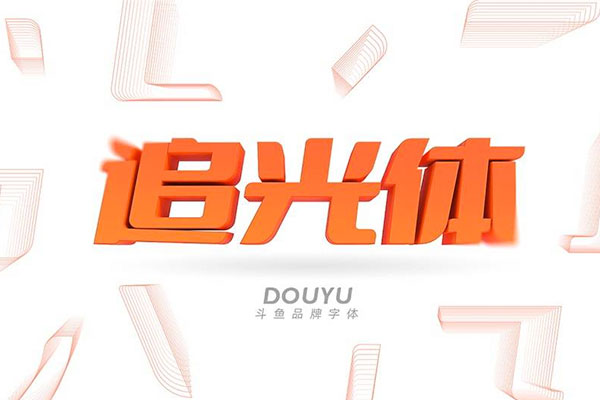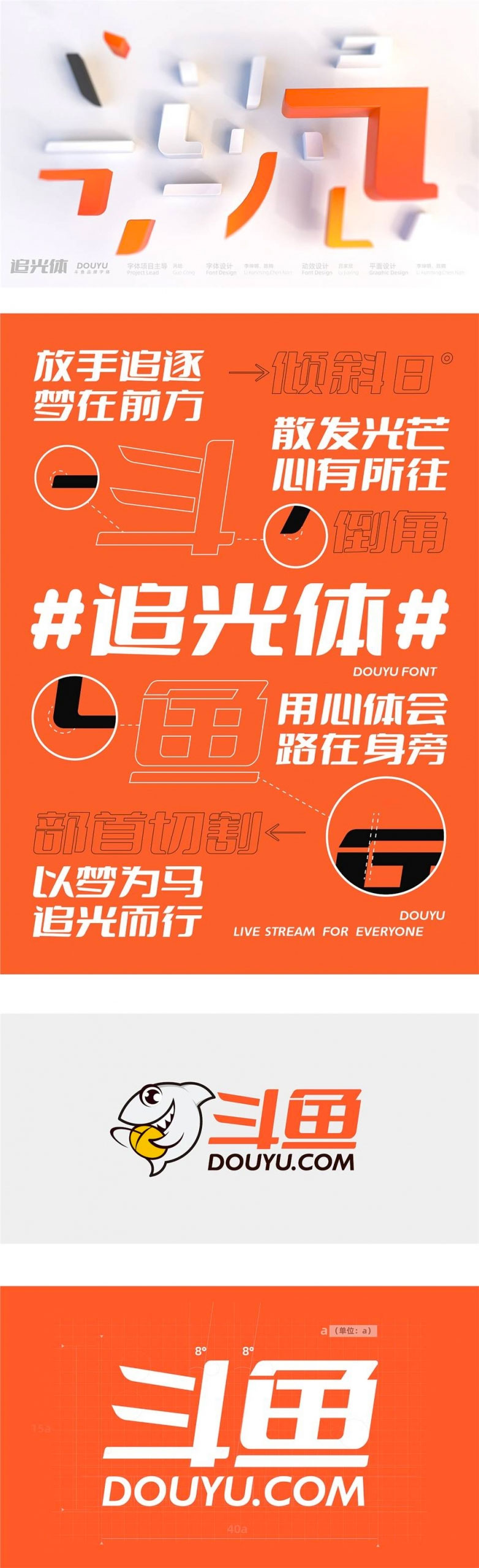
斗鱼追光体
斗鱼追光体:斗鱼武汉研发部UED指导设计的全新品牌字体
斗鱼武汉研发部UED提供了指导,品牌组设计成员精心主导设计的全新品牌字体——斗鱼追光体,它是一种向右8°倾斜的字体,寓意着不断前行的步伐和勇气,以及坚定的目标和梦想。
许多人会问,斗鱼为什么要设计自己的字库?作为一个在国内知名的直播平台公司,我们需要统一的字体来发声,表现企业自身的风格,并且向外界传递我们自己的品牌特质。
斗鱼追光体已于近日上线斗鱼官网,所有用户均可免费下载,并在不同平台上使用。它是符合GB2312简体中文编码字符标准的专属品牌字体,拥有标准版字重,包含6763个中文字符和100个西文及数字符号。随着斗鱼品牌场景的日益丰富,斗鱼追光体能逐渐适配平台的各种场景。